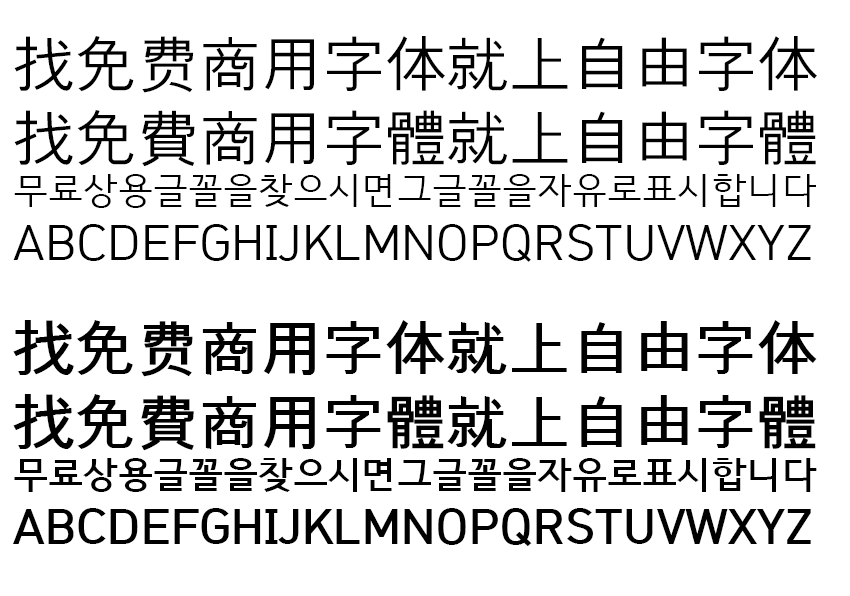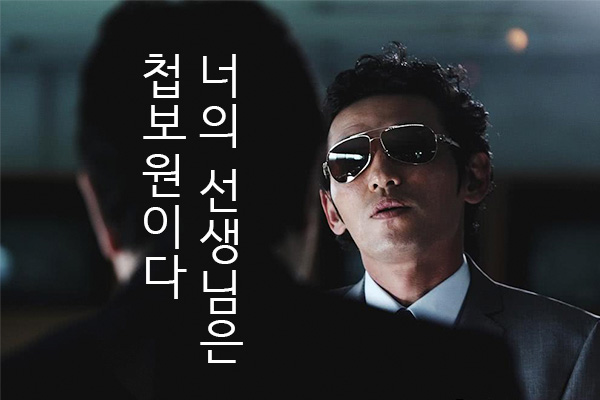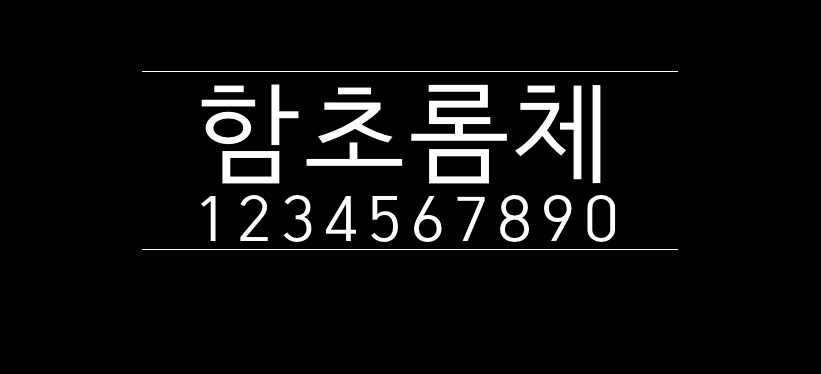
HCR Dotum LVT
HCR Dotum LVT (함초롬돋움 LVT)是一款漂亮韩国旧字形免费商用字体。通过将GSUB / GPOS信息放入Hangul and Computer Corporation的Hamchorom字体中,由韩国技术学会重新分配了该字体。主要目的是在一开始就正确处理旧的韩文。它还具有附带的目的,以使其更容易使用字体中包含的字典药物。
HCR Dotum LVT包含常规和粗体两种字重,它的字符集非常齐全,不光是中文繁体字形,中文简体支持度也非常好!